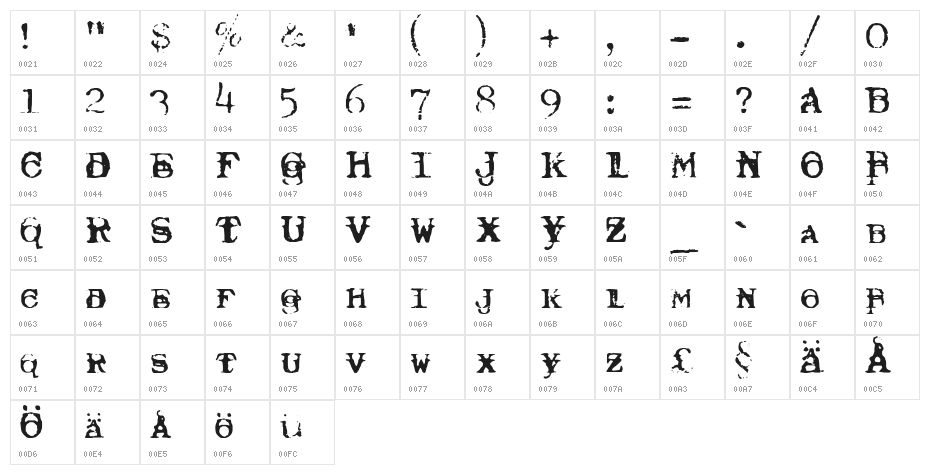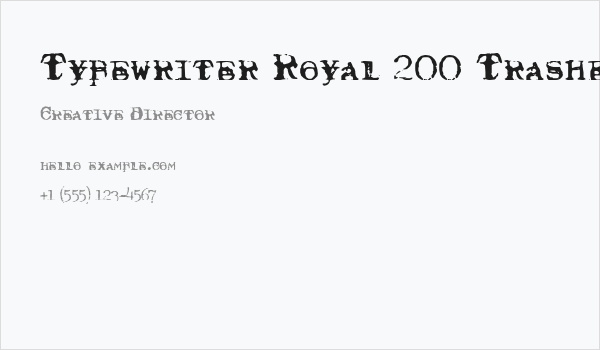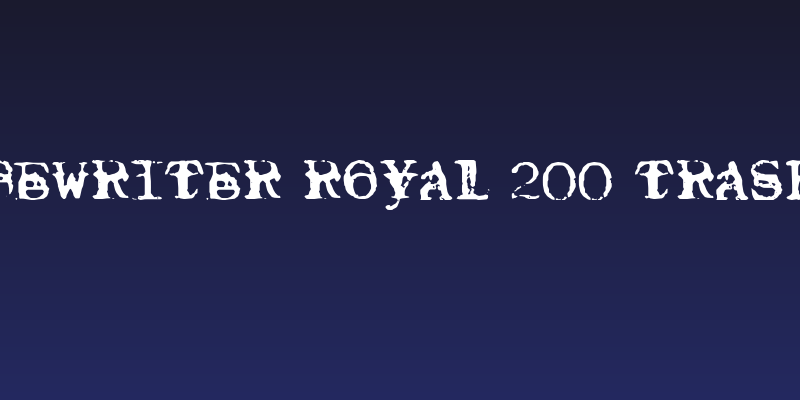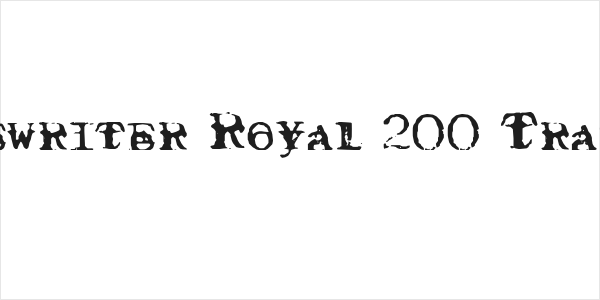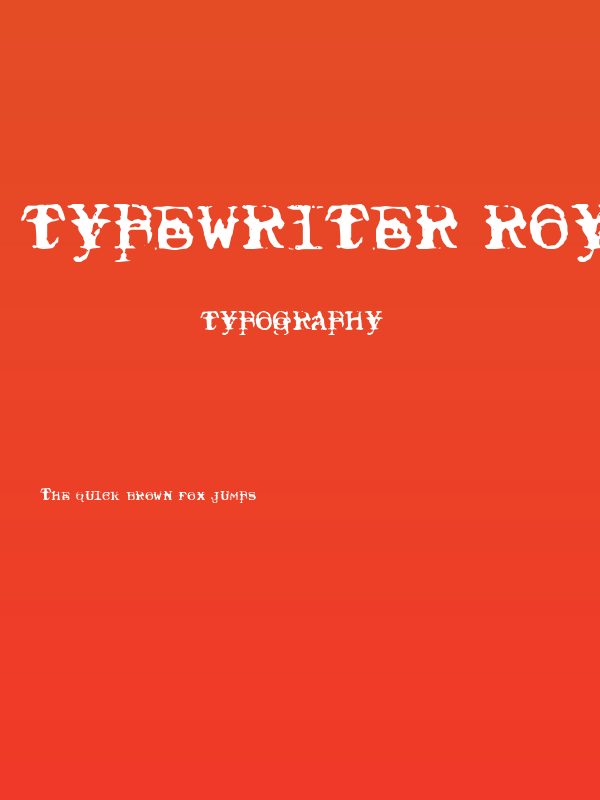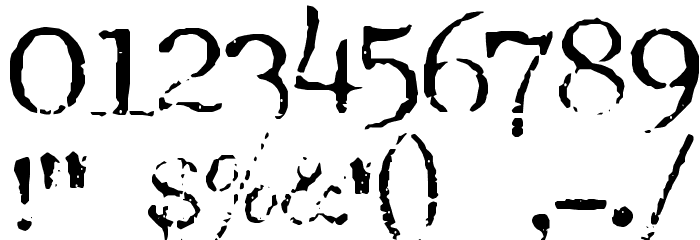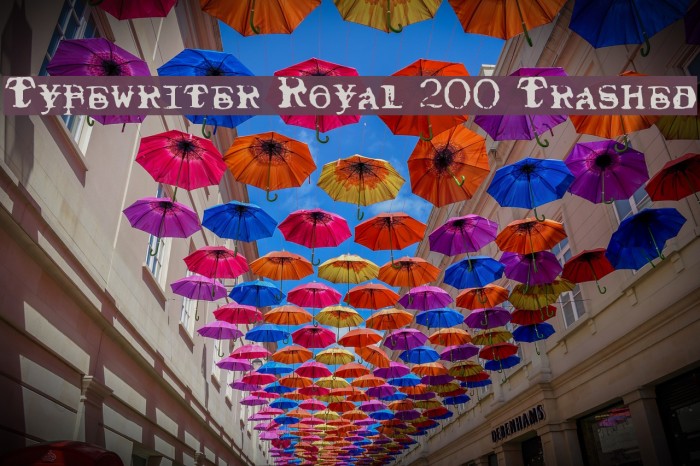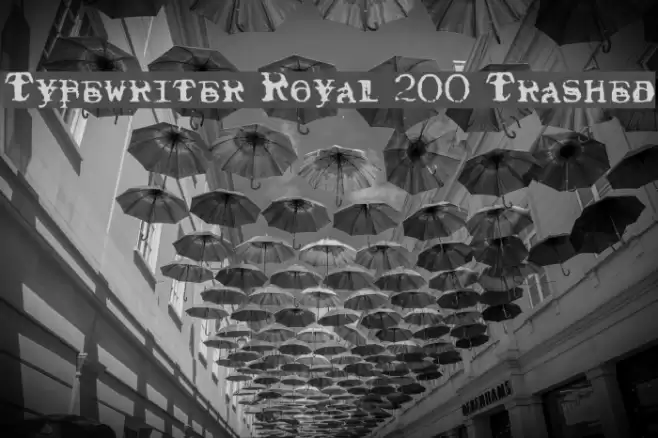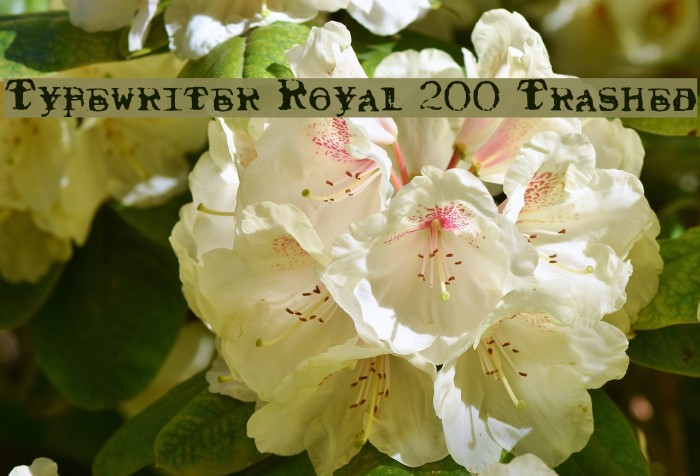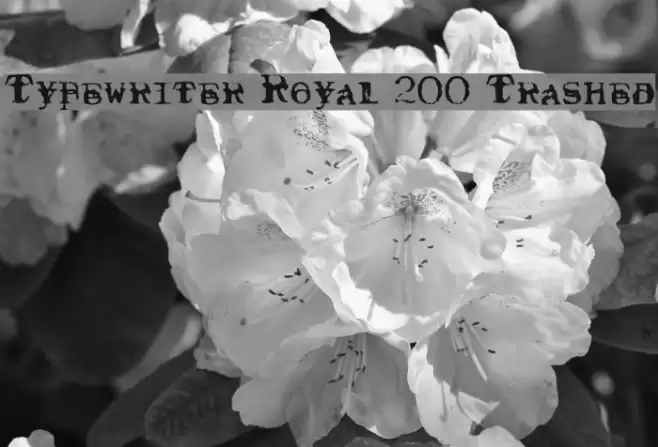
Typewriter Royal 200 Trashed Font
✎ Typewriter
| Gesamtstil | Vintage |
| Vorgeschlagene Projekte | Ideal for retro-themed designs, posters, album covers, and any project seeking a vintage or industrial look. |